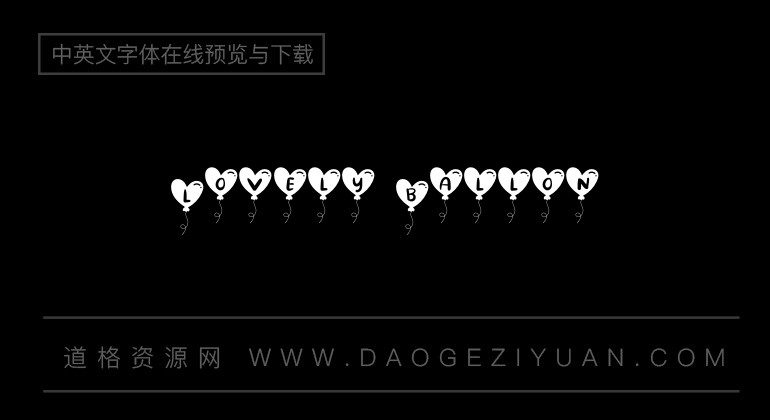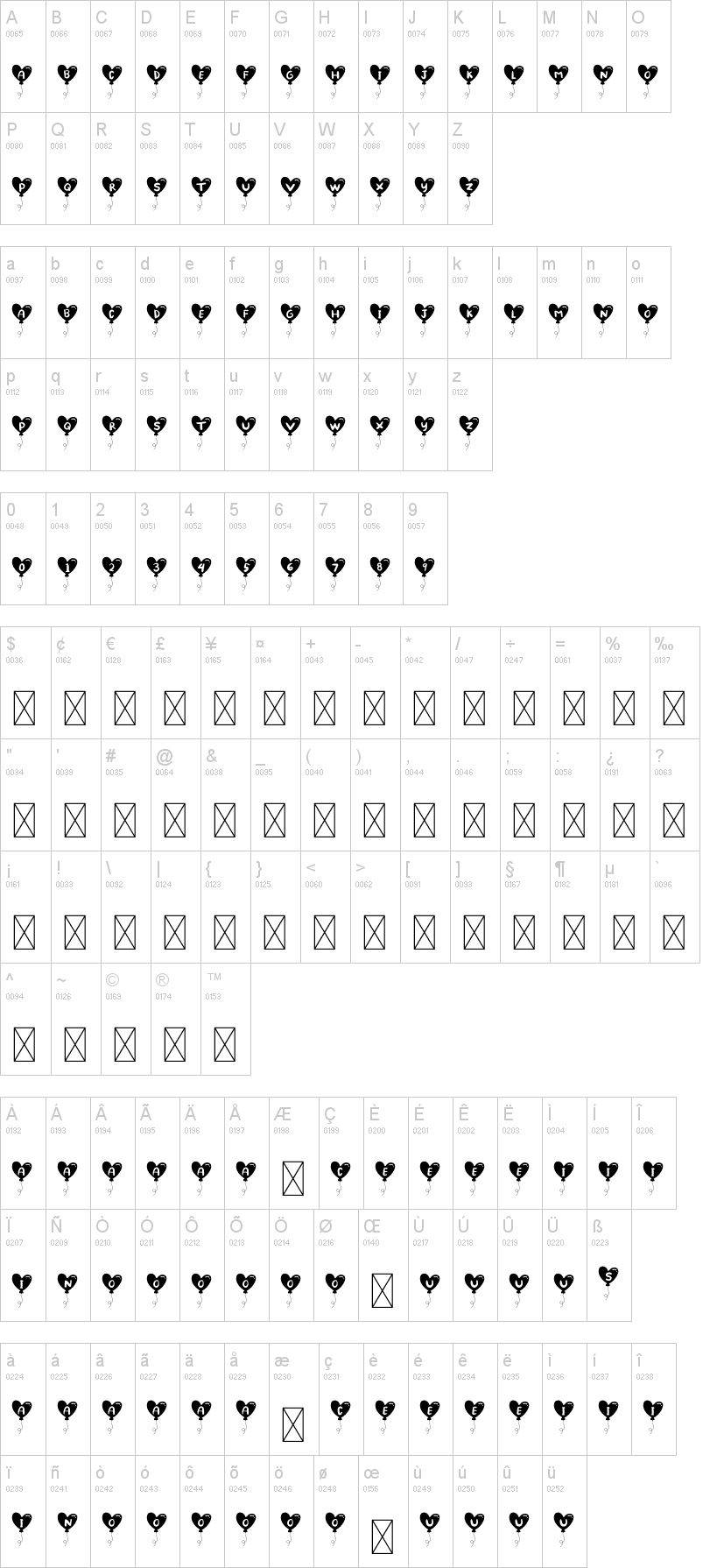
Lovely Ballon
Lovely Balloon 是一款浪漫可爱的字体,它结合了欧式和日式风格,给人以温暖、可爱、活泼的感觉,适合用于婚礼、婚庆、派对等场合的活动主题。它的特点是字体曲线温柔,字形简洁大方,极具时尚感,能够表达出甜蜜的浪漫情怀,是一款非常适合活动主题的字体。
Lovely Ballon是一款非常不错的手写艺术字体,具有很好的视觉感,适合于文化类的宣传设计、商业类品牌的广告和产品包装设计以及个性化文字排版等较多场景。